Crédito devido
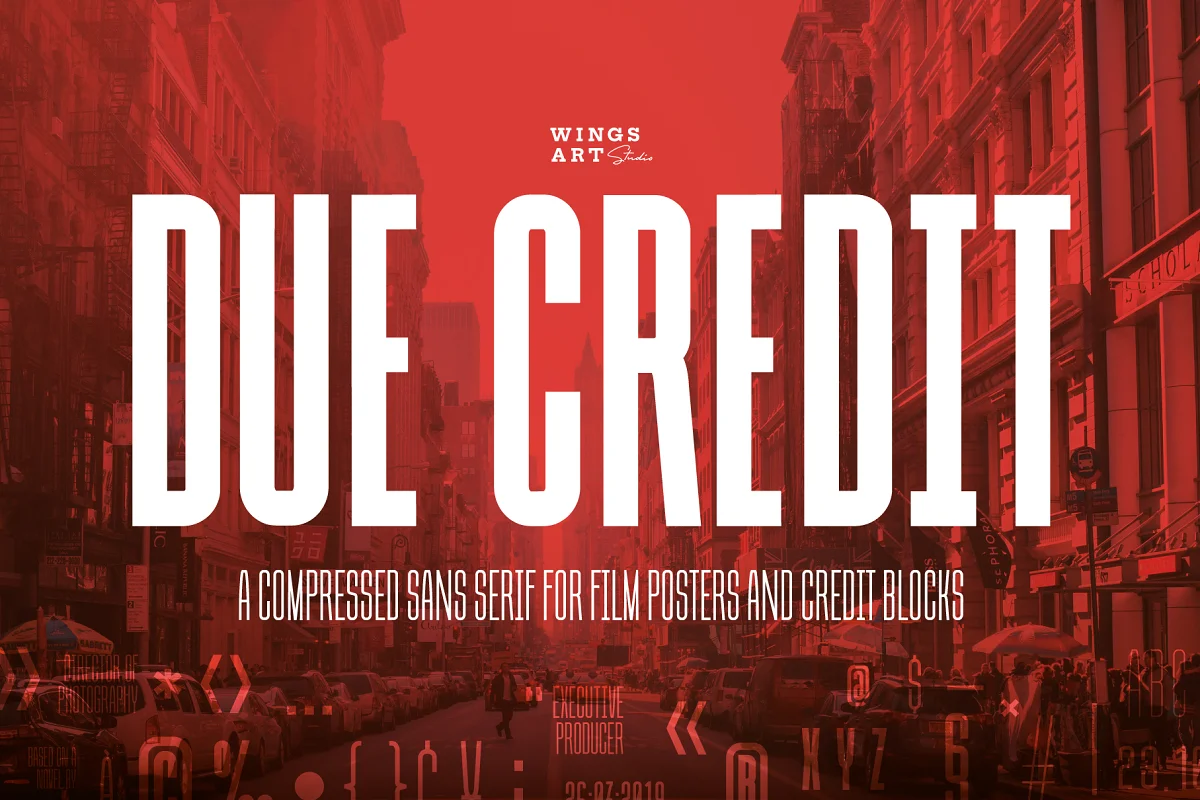
Due Credit é uma nova fonte de exibição excelente projetada para a indústria de cinema e televisão. É um tipo de letra versátil que funciona perfeitamente para títulos em negrito, blocos de crédito, trailers e até pôsteres. O Due Credit oferece um estilo adicional inspirado no terror para ajudá-lo a criar fontes de filmes impressionantes para logotipos, pôsteres e títulos.
Créditos do filme
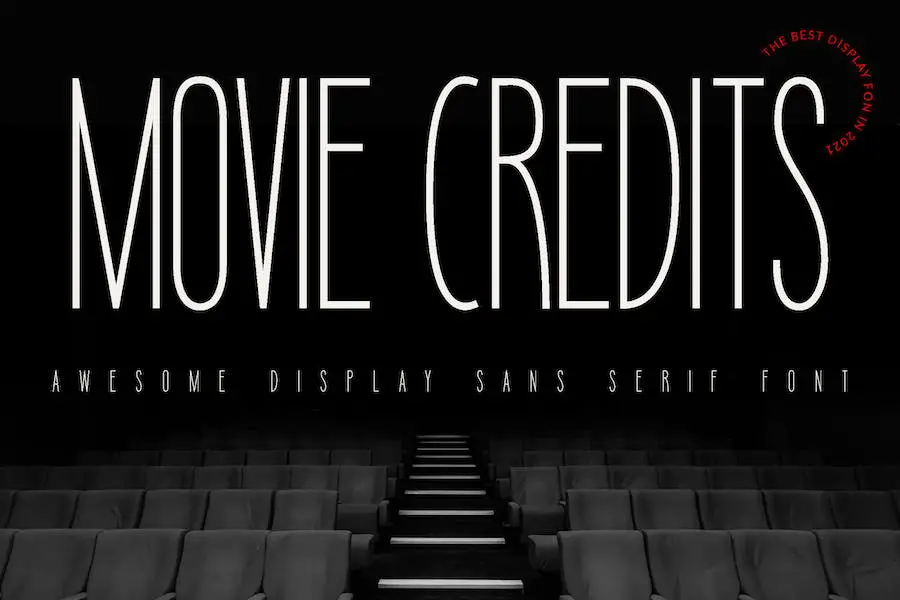
A fonte Movie Credits pode adicionar um pouco de diversão e alegria aos seus designs; é perfeito para pôsteres de filmes, bem como para qualquer projeto que exija um pouco de diversão. Devido à sua simplicidade, é altamente versátil e facilmente adaptável a uma variedade de ideias criativas em uma ampla gama de indústrias.
Suas linhas limpas e ousadia fazem com que pareça profissional, enquanto o espaçamento entre as letras facilita a leitura. Também é fácil personalizar a fonte com diferentes cores, tamanhos e efeitos. Pôsteres e anúncios de filmes precisam desses recursos, por isso são incríveis de fazer.
A fonte Movie Credits é uma excelente escolha para designers gráficos que desejam melhorar a aparência de seus projetos. Ao procurar fontes de filmes para pôsteres, Movie Credits é a fonte perfeita porque captura a verdadeira essência desse gênero. O Movie Credits certamente fará seu trabalho se destacar com seu design divertido e profissional.
OS SONNY FIVE
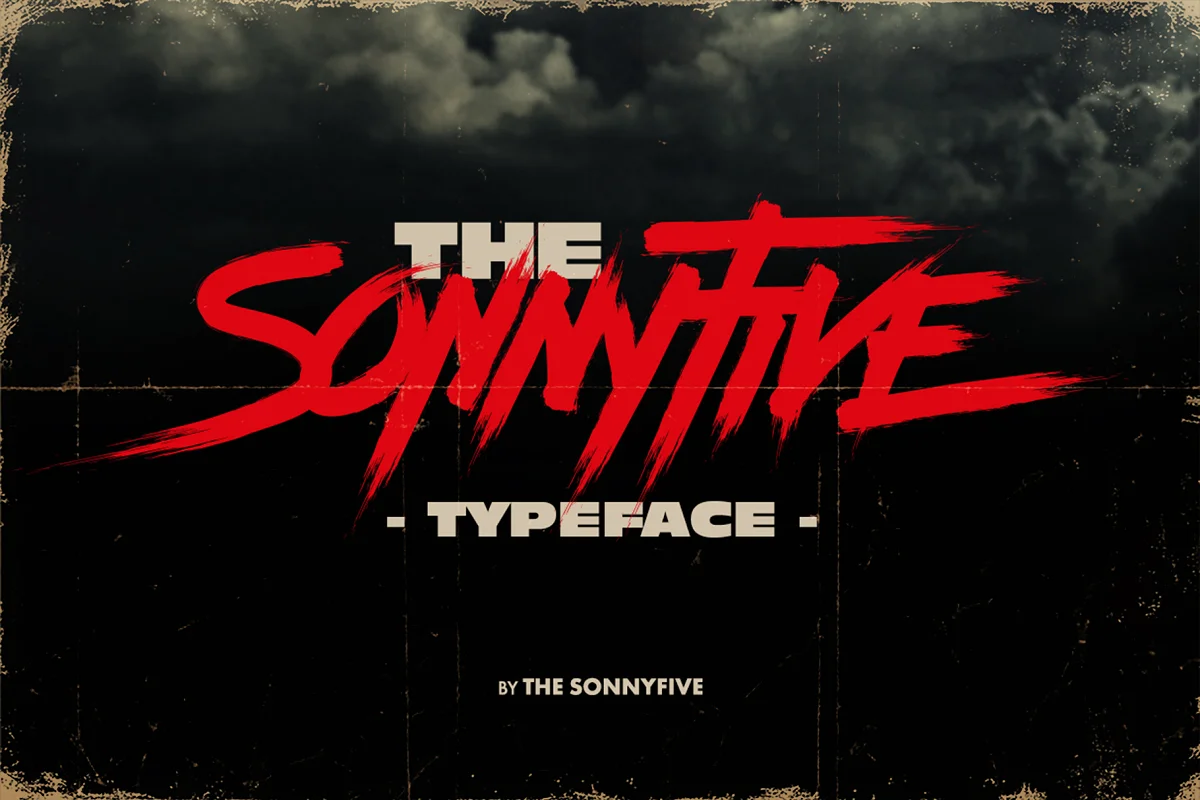
O SonnyFive é uma fonte de pincel que foi projetada especificamente para pôsteres de filmes de terror nos anos oitenta. Essa fonte também pode ser usada para outros fins, mas é mais adequada para criar uma atmosfera estranha e assustadora.
As letras maiúsculas e minúsculas, juntamente com numerais e pontuações, fornecem tudo o que você precisa para criar um design coeso. Além disso, o SonnyFive inclui letras húngaras, o que o torna versátil também para o público internacional.
Você deve pensar em The SonnyFive se estiver procurando por um estilo retrô e cheio de personagens que adicionará personalidade ao seu design com tema de terror. Seu estilo único fará com que seu projeto pareça mais autêntico e envolvente do que qualquer outra coisa.
Búfalo
Como uma fonte manuscrita única e interessante, a Buffallo é perfeita para adicionar personalidade e criatividade a qualquer tipo de projeto de design. Ele atende a uma ampla variedade de requisitos de design, tornando-o um item essencial para designers gráficos que desejam aprimorar sua criatividade em seus projetos.
Com Buffallo, você obtém arquivos de fonte OTF e TTF, que são codificados por PUA. Isso significa que a fonte pode ser acessada no Adobe Illustrator, Adobe Photoshop, Adobe InDesign e até no Microsoft Word.
Assistido
Se você deseja adicionar um toque único e peculiar aos títulos de seus filmes, Watched é a fonte para você. Watched é caracterizado por variações de letras maiúsculas e combinações de minúsculas que criam um estilo de escrita interessante. Com seu toque descontraído, seu projeto se destacará.